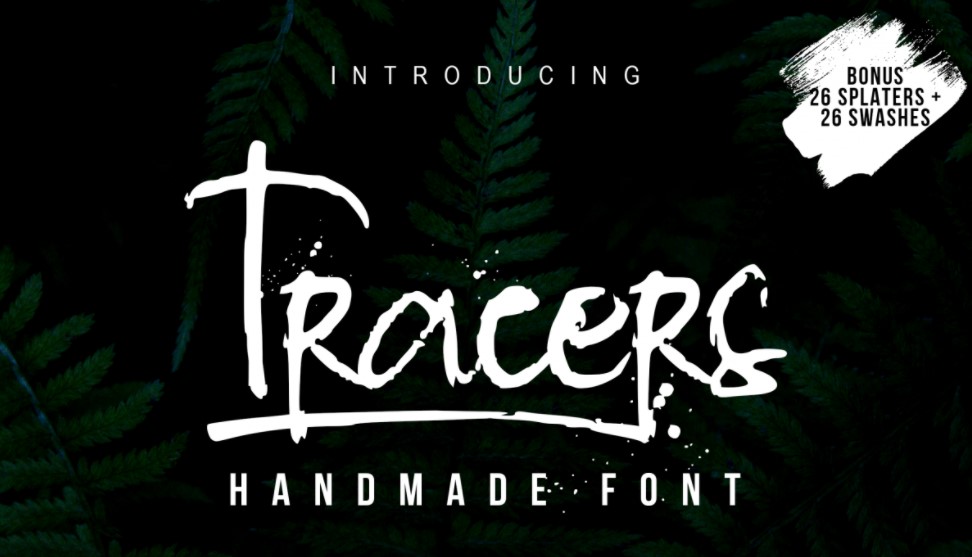
Fontbundles Tracers - Handmade Script Font
[Fontbundles] Tracers - Handmade Script Font
Tracers - это рукописный шрифт, созданный вручную, который идеально сочетается и позволяет быстро и легко создавать потрясающие рукописные надписи. Также включены 26 бонусных ударов и 26 бонусных сплаттеров, идеально подходящих для придания вашему тексту последнего штриха изящества!
1. Прописные и строчные буквы
2. Большой набор знаков препинания, цифр и поддерживает международные языки
3. Также доступны стилистические альтернативы для нескольких ключевых строчных букв.
5. Бонус 26 ударов и 26 брызг